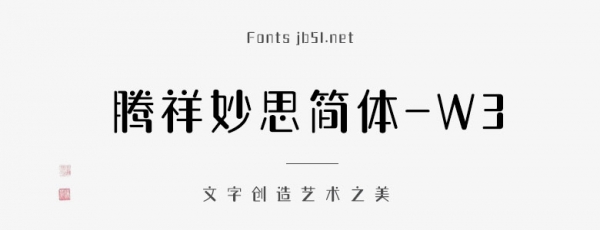
騰祥妙思簡體-W3是一款不錯的藝術(shù)字體,由騰祥字庫出品,筆畫斷連輾轉(zhuǎn),粗細藏露變化,相映成趣;字形俊雅,風格獨特,適合應(yīng)用于藝術(shù)設(shè)計、平面宣傳設(shè)計、網(wǎng)頁設(shè)計,書法字帖等領(lǐng)域,需要的朋友可以前來本站下載。
此款字風格為美術(shù)字體。妙思W3為系列字庫中較粗一款,適用于標題、小標題及正文。筆畫斷連輾轉(zhuǎn),粗細藏露變化,相映成趣;字形俊雅,風格獨特;筆畫凝練簡潔巧妙構(gòu)思、字形結(jié)構(gòu)修長、整幅字給人以樸實無華,清新秀麗之感。設(shè)計師以輕松的筆調(diào)詮釋出整款字體的風韻,筆畫聚散有致,沉靜閑適,妙語空傳醉墨香……
本作品可適用于數(shù)字媒體、印刷出版、包裝設(shè)計、兒童讀物、廣告設(shè)計、網(wǎng)頁設(shè)計等。